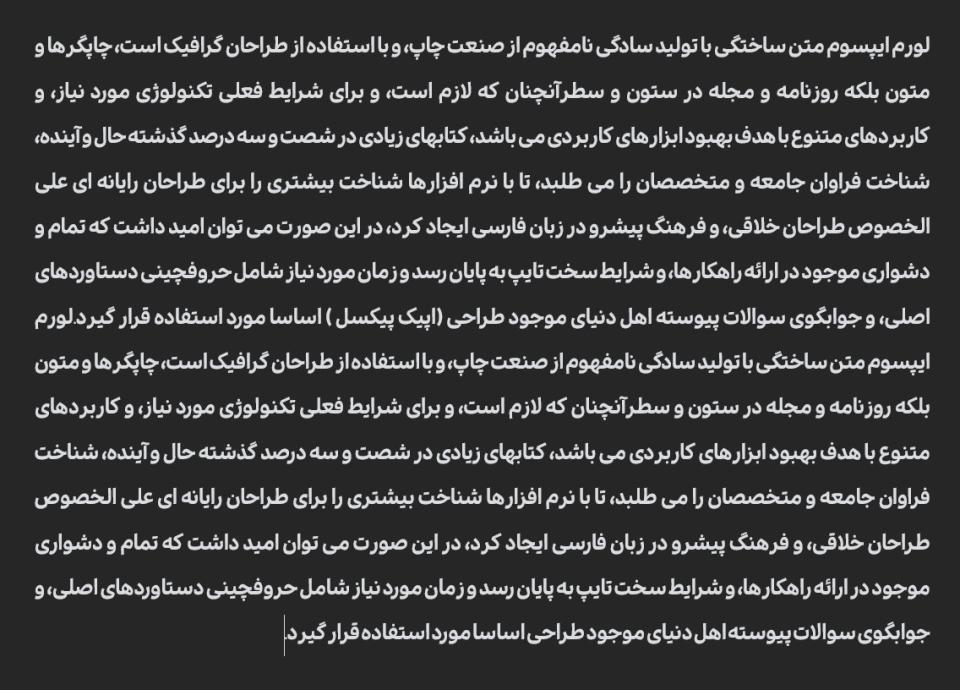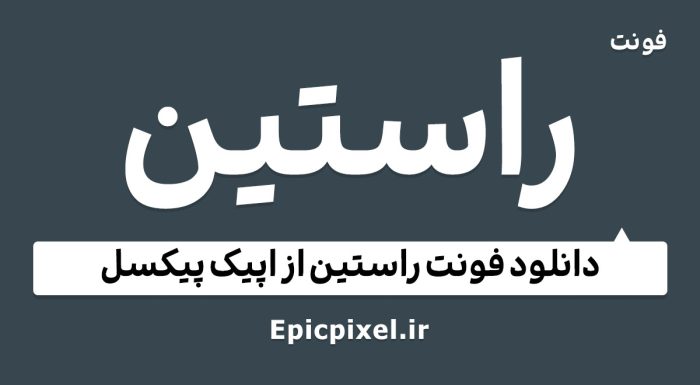
2 فونت راستین فارسی Rastin
فونت راستین فارسی با طراحی ساده و خوانا، برای انواع پروژه ها از متون چاپی تا دیجیتال، گزینه ای ایده آل است. این فونت رایگان به شما این امکان را می دهد که بدون نیاز به پرداخت هزینه ای، از زیبایی و کارایی آن بهره مند شوید.
یکی از ویژگی های برجسته راستین، تنوع ضخامت ها و سبک هاست که امکان استفاده در عناوین، بدنه متن ها و حتی پروژه های گرافیکی را فراهم می کند. این فونت با ترکیب خطوط نرم و گوشه دار، جلوه ای خاص به متون شما می بخشد و جذابیت بصری ایجاد می کند.
فونت راستین فارسی از نظر کاراکترها کامل است و تمامی حروف فارسی و عربی را پشتیبانی می کند، که این ویژگی برای طراحان و نویسندگان اهمیت زیادی دارد. همچنین، طراحی منظم و دقیق آن باعث افزایش سرعت خواندن و کاهش خستگی چشم می شود.
استفاده از فونت راستین فارسی در متون دیجیتال و چاپی، تجربه ای حرفه ای و کاربرپسند برای شما به ارمغان می آورد. این فونت با قابلیت استفاده در نرم افزارهای مختلف و سازگاری با استانداردهای وب، گزینه ای ایده آل برای طراحان وب و گرافیک است. دانلود و استفاده از فونت راستین، به پروژه های شما زیبایی و کیفیت می بخشد و باعث جلب توجه بیشتر مخاطبان می شود.